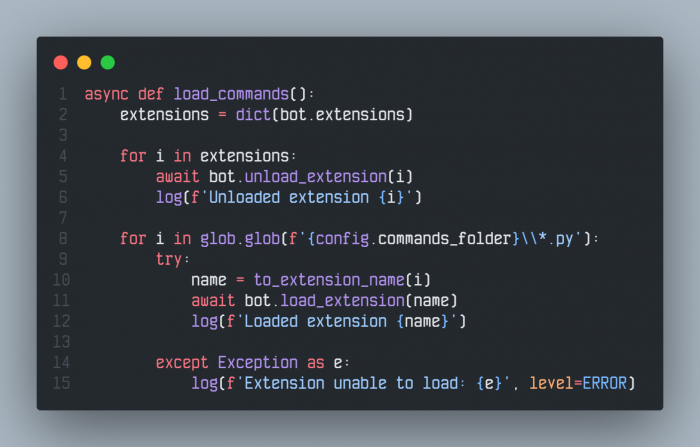
Отличный шрифт! Хотелось бы только в кириллице более симметричную Дд, с ножками как у ЦЩ, более широкою Цц, верхний вынос (пламневидный элемент) у б до правого конца буквы и загнутую вверх с обеих сторон кратку у Йй. Ещё у буквы Гг делают нижнюю засечку, как у frli, в моноширинных шрифтах, штобы она такой широкой не была, но это на твоё усмотрение. С наступающим!)